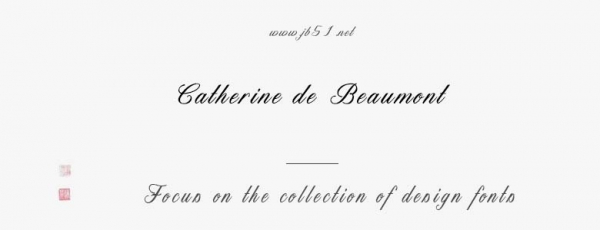
Catherine de Beaumont英文書法字體,筆觸略細(xì),字形優(yōu)美,具有很好的視覺感,適合應(yīng)用于藝術(shù)設(shè)計(jì)、平面宣傳設(shè)計(jì)、網(wǎng)頁設(shè)計(jì),書法字帖等領(lǐng)域。有需要的朋友快來本站下載使用吧。